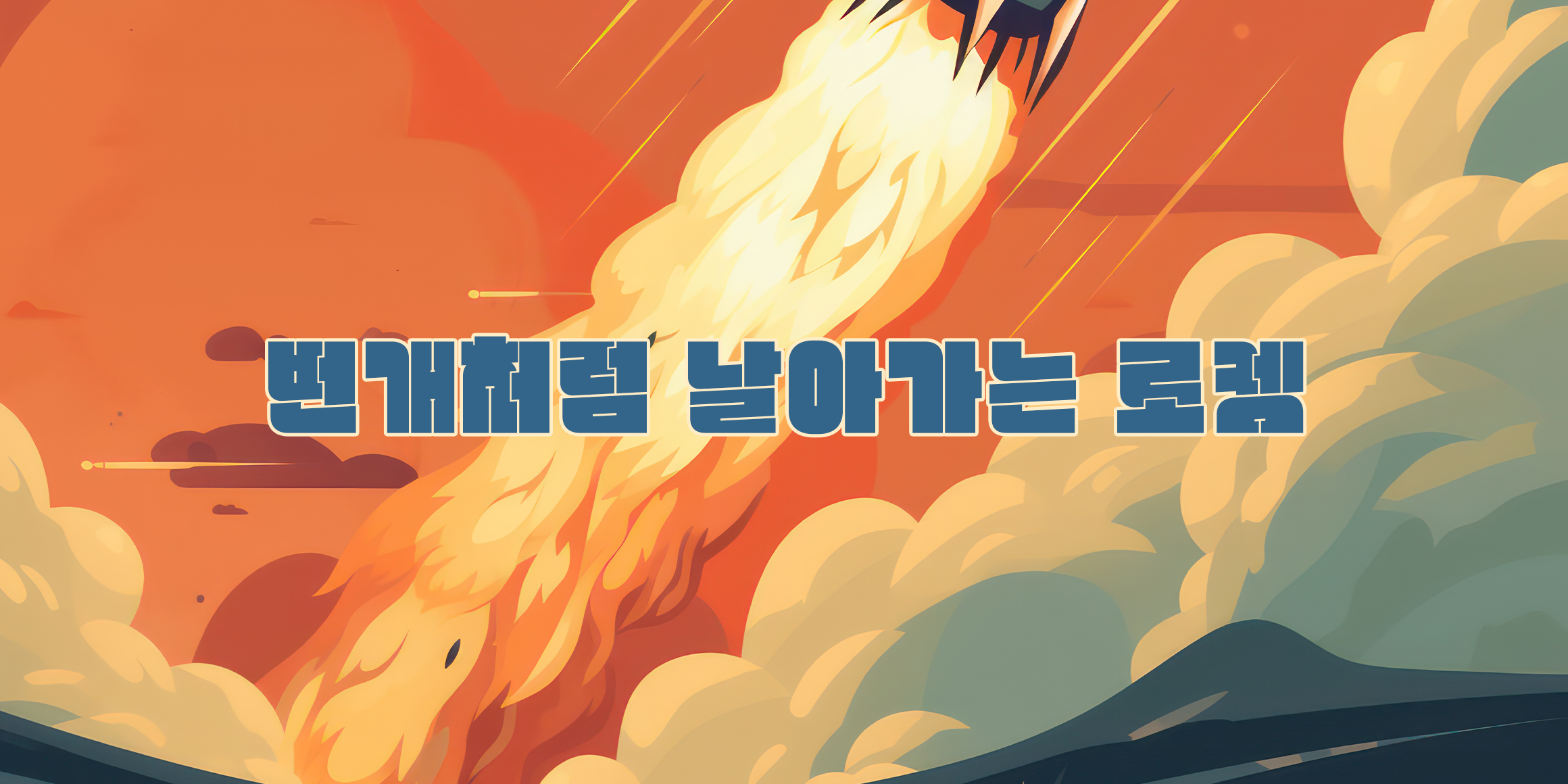
DR대약진
대약진(daeyagjin)체는 장체 스타일의 복고풍 디자인을 특징으로 하는 감각적인 폰트로, 다양한 디자인 분야에서 활용될 수 있는 특성을 가지고 있습니다. 굵기의 비율에 따른 4개의 숫자로 표현된 패밀리는 주목성 강조로 브랜딩 및 디자인 프로젝트에 적합합니다. 광고, 웹디자인, 포장디자인, 출판물 등 다양한 매체에서 독창적이고 강렬한 시각적 효과를 낼 수 있습니다.